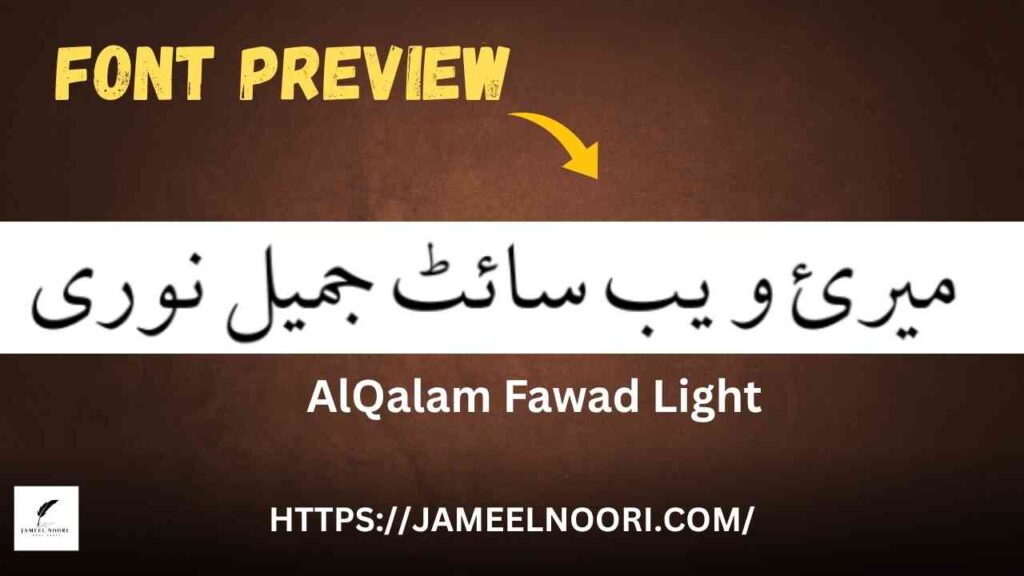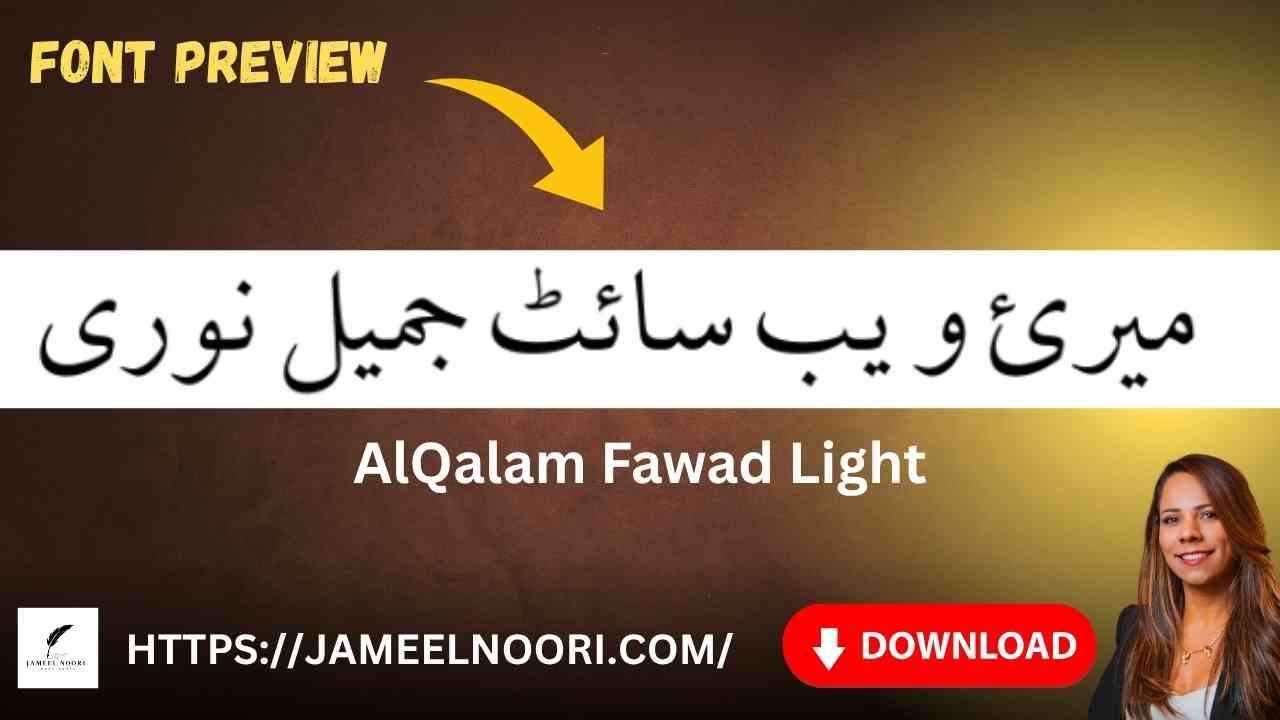
Introduction – Urdu Font AlQalam Fawad Light Kya Hai?
AlQalam Fawad Light Urdu Font ek khubsurat aur halka-weight TrueType Nastaleeq Urdu font hai, jo un logon ke liye design kiya gaya hai jo Urdu likhne mein nazakat aur readability chahte hain. Yeh font aise users ke liye ideal hai jo graphic design ya Urdu typing mein elegance ko tarjeeh dete hain.
Font Ki Tafseelat – AlQalam Fawad Light
| Font Name | AlQalam Fawad Light |
| Font Style | Light Nastaleeq |
AlQalam Fawad Light Font Ke Features
- ✅ Light & elegant Nastaleeq font
- ✅ Best for Urdu web content, poetry, and social media posts
- ✅ Highly readable with sleek design
AlQalam Fawad Light Font Kahan Use Kar Sakte Hain?
Yeh font bohat se mukhtalif platforms par use hota hai, jaise:
- ✒️ Urdu Shayari aur Nazmein likhne ke liye
- 📕 Educational PDFs aur Urdu books
- 🎨 Social media quotes & graphics
- 📝 Urdu blog posts ya web writing
- 📰 Headlines aur sub-headings for websites
Conclusion – Urdu Likhiye Khubsurti ke Sath
Agar aapko chahiye ek nazakat bhara, readable aur stylish Urdu font, to AlQalam Fawad Light font aapke liye perfect hai. Isay aaj hi download karein aur apne Urdu projects ko ek naya look dein.